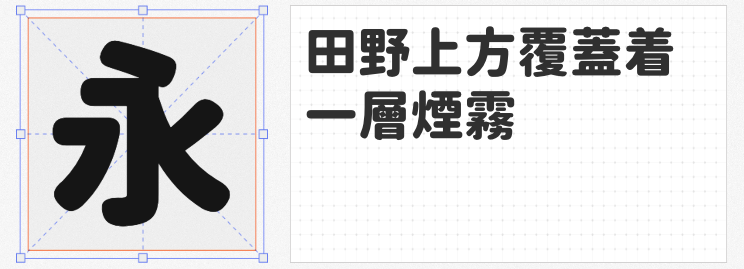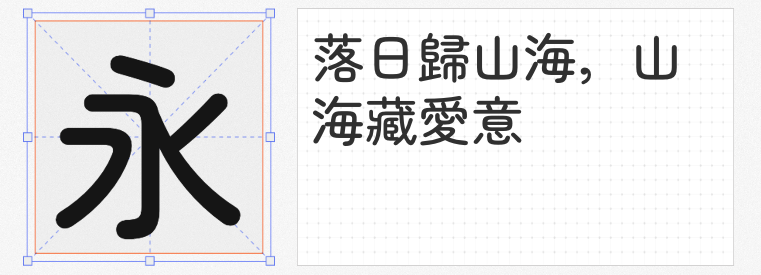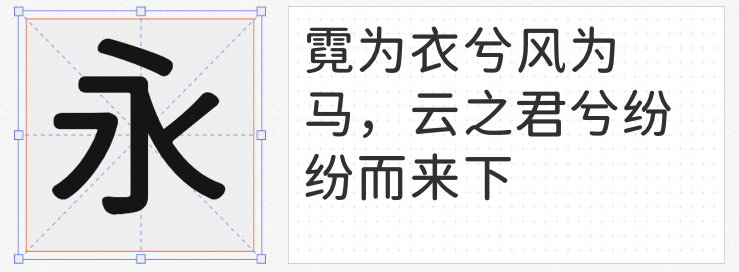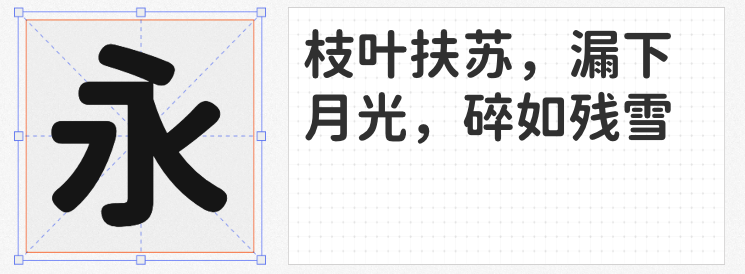
在视觉设计中,圆体字以其流畅的笔画和温润的视觉感受,成为传递亲和力与现代感的核心元素。本文精选四款开源免费且可商用的圆体字库,从设计背景到应用场景,为设计师提供实用指南。
作为思源黑体的圆体分支,「源泉圆体」通过自动化脚本将黑体笔画全部圆角化,并增加封闭区域的内圆角处理。其Heavy版本采用900字重,笔画粗细对比强烈,适合作为标题字体使用。该字体支持繁简中文、日文及西里尔字母,在海报设计、动态图形及UI标题中能快速建立视觉焦点。
基于狮尾圆体改造的975圆体,通过缩小字面至97.5%并微调字重,优化了小字号下的显示效果。其笔画粗细过渡自然,西文部分搭配Baloo 2字体形成风格统一的中西混排方案。作为SIL Open Font License授权字体,975圆体在社交媒体图文、移动端H5及电子书设计中表现出色,尤其适合需要长时间阅读的场景。
基于日本Zen Maru Gothic调整的寒蝉半圆体,通过优化笔画转角弧度,创造出温润而不失现代感的视觉效果。该字体采用中庸的字重设计,既可胜任正文排版,也能通过字号调整作为副标题使用。其开源协议允许商业用途,在文创产品、儿童读物及轻食包装等领域展现出独特优势。